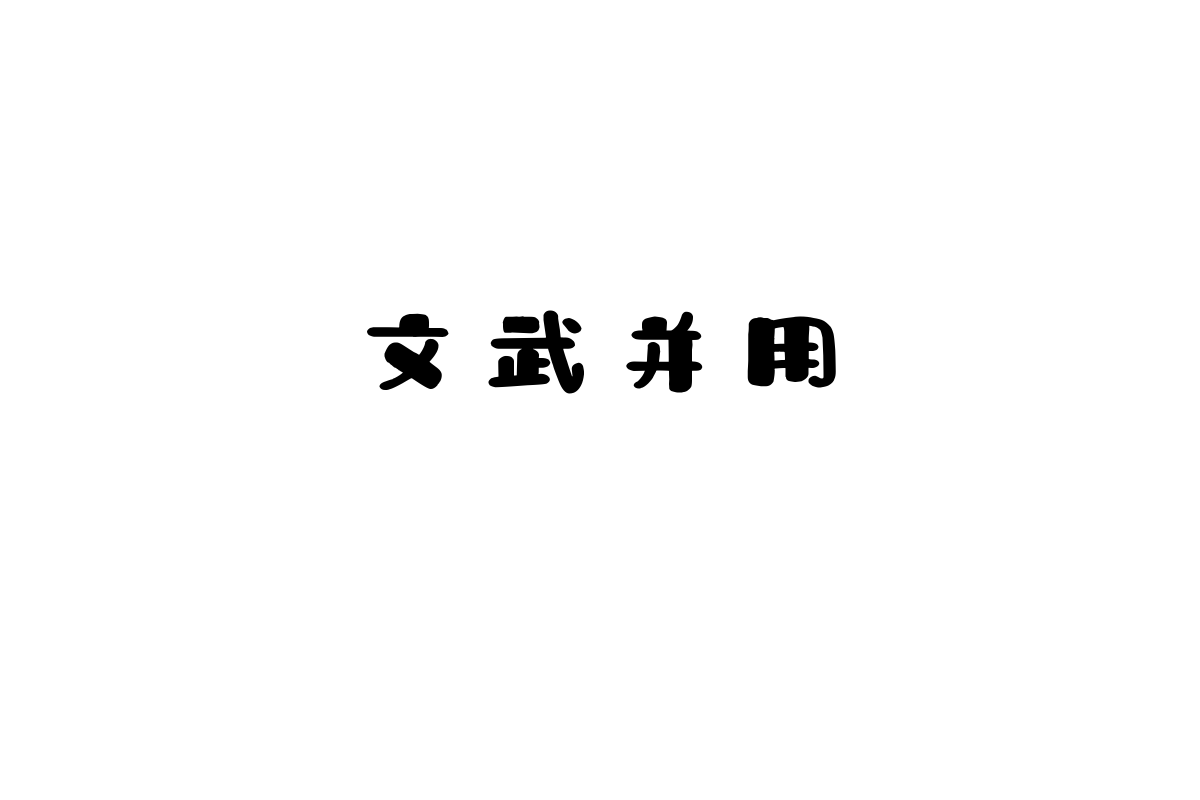
“也字工厂”是一个专注于创意字体设计的工作室,致力于探索和实现文字的无限可能。我们的目标是通过创新的设计,将文字转化为一种艺术形式,让每一个字符都充满生命力和个性。
我们的设计理念是“也字工厂马戏团”,灵感来源于马戏团这种充满活力和创造力的表演场所。在这个舞台上,各种动物、人物和道具共同演绎着精彩的表演,而我们也希望通过设计,让文字成为这个舞台上的主角,展现出独特的魅力和风采。
我们的字体设计风格独特,既有现代感又不失传统韵味。我们注重细节的处理,力求让每个字符都清晰可辨,同时又不失趣味性和想象力。无论是优雅的手写体,还是奔放的卡通风格,我们都可以尝试,以满足不同场景下的需求。
我们相信,一个好的字体设计不仅仅是为了美观,更是为了传递信息和情感。因此,我们在设计时会充分考虑到文字的含义和语境,确保每个字符都能准确传达出其应有的意义。
总之,“也字工厂马戏团”是一个充满创意和活力的字体设计工作室。我们期待与您一起探索文字的无限可能,为您的项目带来独特的视觉体验。